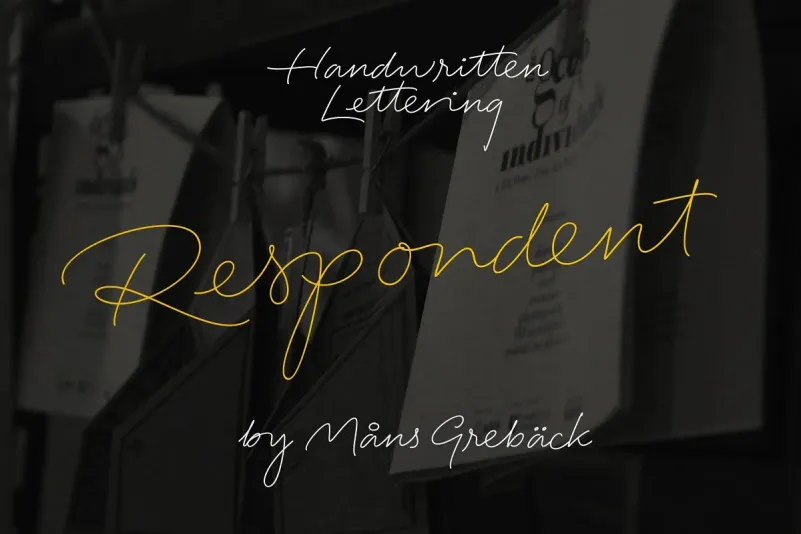
Respondent Handwritten Font – Download Grátis
A fonte ‘Respondent Handwritten Font’ é uma família script leve e simples criada por Mans Greback em 2021. Seu estilo é intrigante e atraente, combinando características autênticas e empáticas com um toque selvagem e vibrante. Ideal para textos de destaque ou mensagens pessoais, essa fonte oferece uma maneira única de adicionar personalidade a qualquer projeto, seja em aplicativos de redes sociais, websites, cartões de aniversário ou até mesmo em designs gráficos digitais. Com sua característica leve e elegante, ela é perfeita para criações que buscam expressar emoção através do texto. Um verdadeiro recurso para designers buscando estilizar seus projetos de maneira única e autêntica.